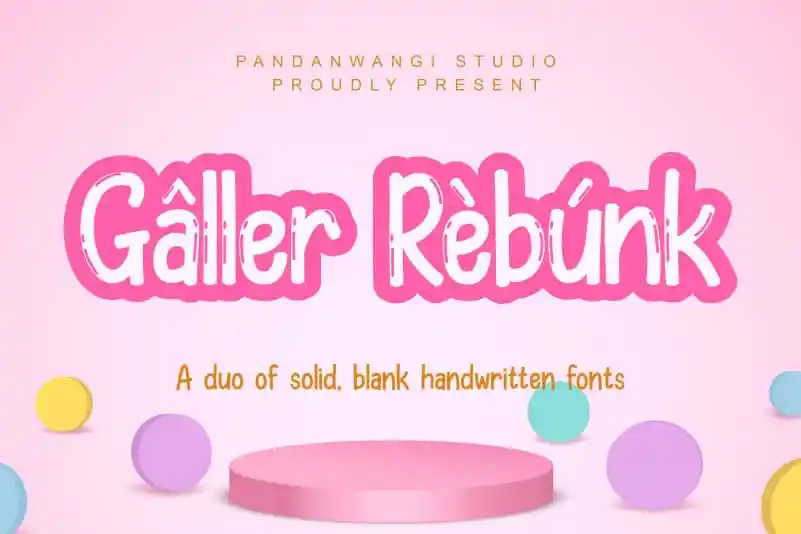
Galler Rebunk Font – Fonte Grátis
Galler Rebunk Font
A Galler Rebunk Font é uma fonte escrita a mão com um toque suave e amigável que possui dois formatos sólidos e estampados. Esta fonte escrita a mão brilhante transformará qualquer ideia criativa numa destaque única. O seu estilo natural e único faz dela perfeitamente adequada para grandes designs de piscina. Inspire-se em sua autenticidade, utilize-a para criar cartões de convidado encantadores, arte de papelaria bonita, postagens sociais chamativas e cartões de boas-vindas fofos. O único limite é sua imaginação!